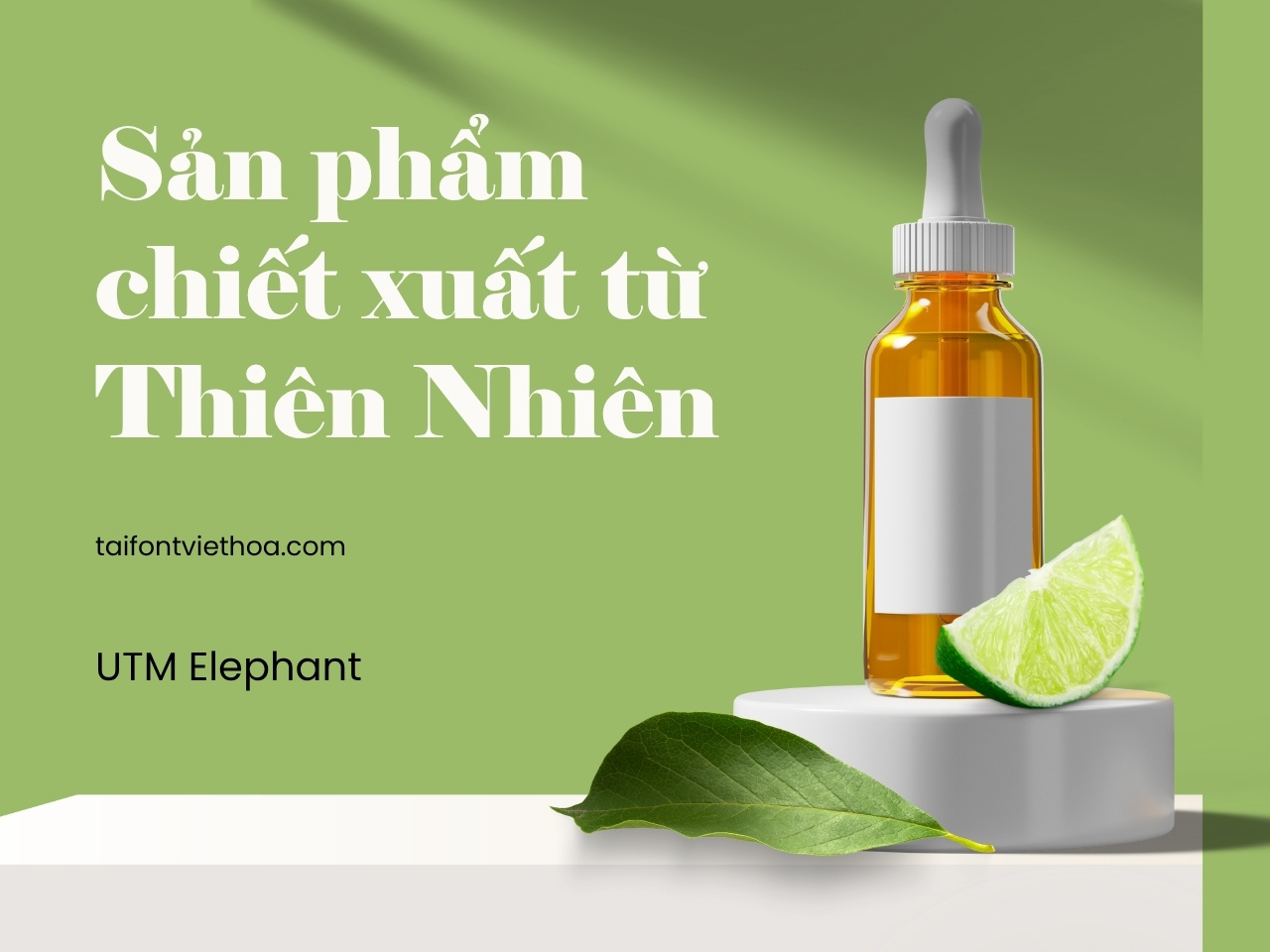
Giới thiệu về font UTM Elephant
UTM Elephant là phiên bản Việt hóa của font Elephant – một kiểu chữ serif đậm nét, mạnh mẽ và nổi bật, được thiết kế để tạo sự ấn tượng và thu hút trong các dự án thiết kế. Font gốc nổi bật với các nét chữ có chân (serif) dày dặn, vuông vức và tỷ lệ cân đối, phù hợp cho tiêu đề, bảng hiệu và các thiết kế cần sự nổi bật và trang trọng. Phiên bản Việt hóa đã được hoàn thiện để hỗ trợ đầy đủ tiếng Việt cùng hơn 200 ngôn ngữ khác, mở rộng khả năng sử dụng trong nhiều lĩnh vực thiết kế chuyên nghiệp.
Đặc điểm thiết kế và ứng dụng của UTM Elephant
UTM Elephant sở hữu cấu trúc serif với các nét chân chữ dày dặn, vuông vức và độ tương phản cao. Font có thiết kế chắc chắn, dễ đọc và tạo hiệu ứng thị giác mạnh mẽ, rất phù hợp cho tiêu đề, logo và các thiết kế cần sự ấn tượng. Font còn được trang bị nhiều ligature và glyph thay thế giúp tăng tính linh hoạt trong thiết kế.
Font thích hợp sử dụng trong thiết kế sách, tạp chí, thiệp cưới, danh thiếp, bao bì sản phẩm cao cấp và các ấn phẩm thương hiệu sang trọng. Các ngành nghề phù hợp gồm: xuất bản, nghệ thuật, thời trang, tổ chức sự kiện, giáo dục và thiết kế nội thất.